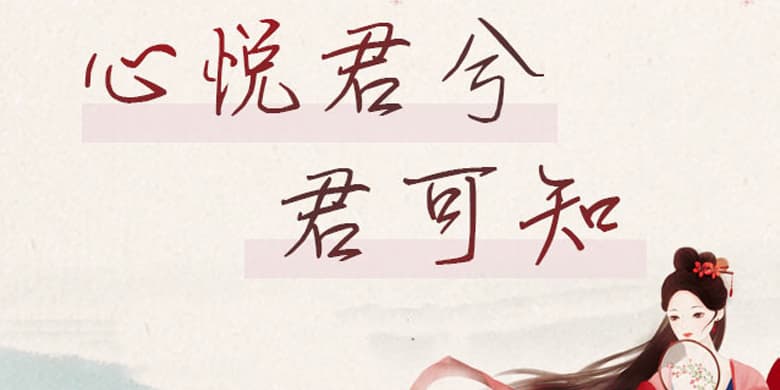
品牌:方正手迹设计师:王航发行时间:2020字库编码:简繁扩展(GBK)分类:常规书写·硬笔字体属性:精品字
随着现代通信技术的发展,现代人很少去用书信去表达情感,而又极少数人能在书写的字上去寄拖自己的心情。心悦君兮君可知做到了以字传情,果断的起笔方式,恰到好处的丝连,洒脱的勾法等等。适用于文艺类的书刊、品牌广告和产品包装设计,以及社交网络的个性化用字。